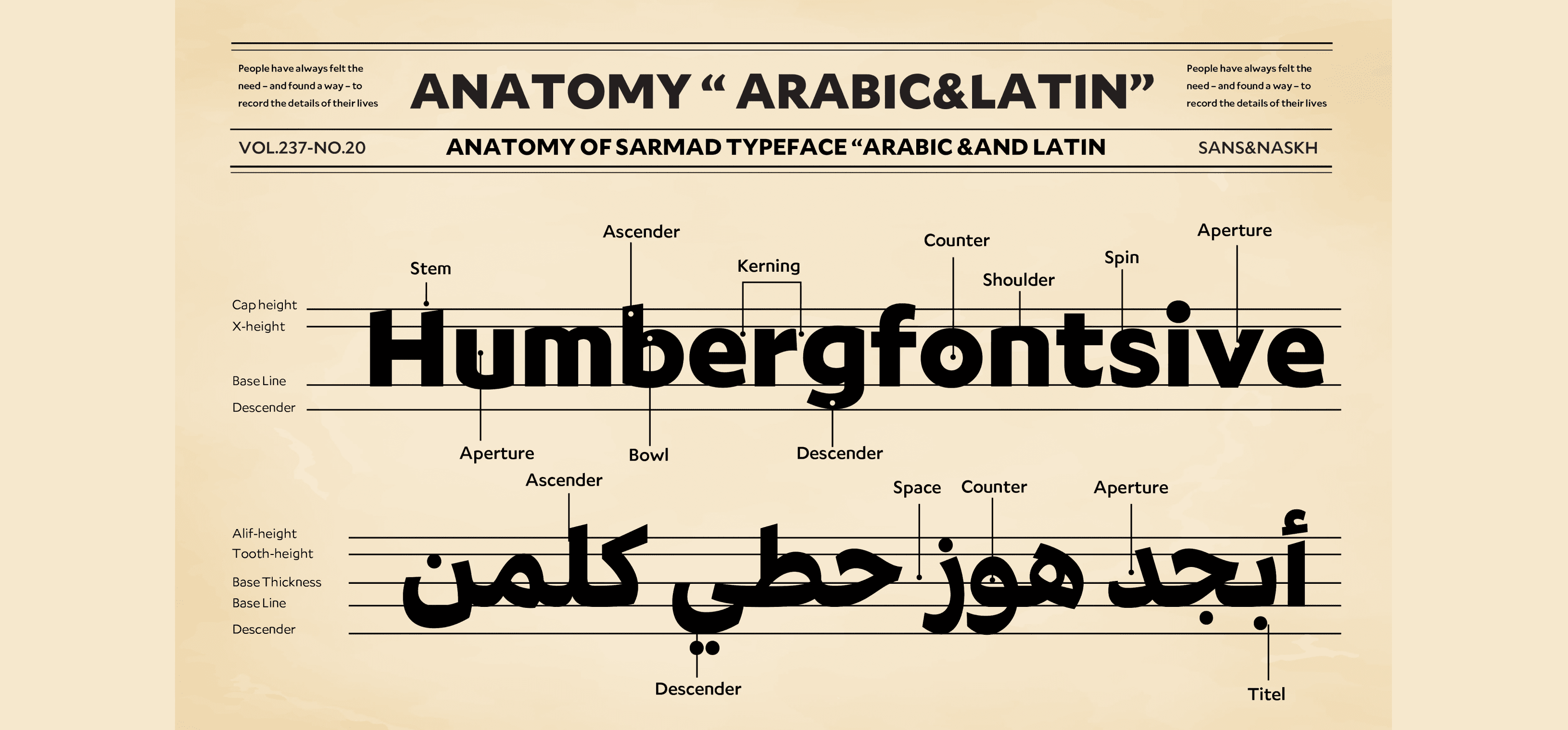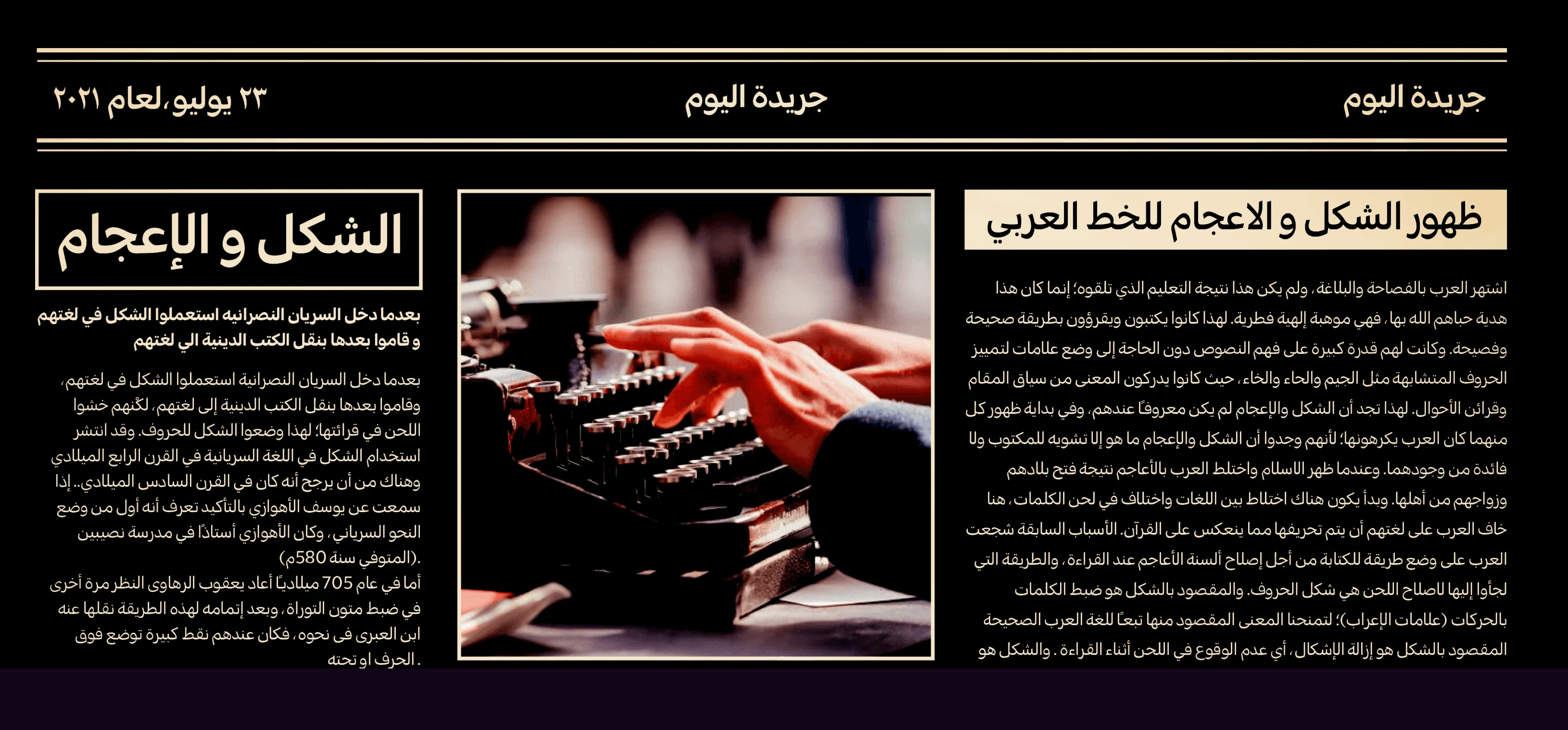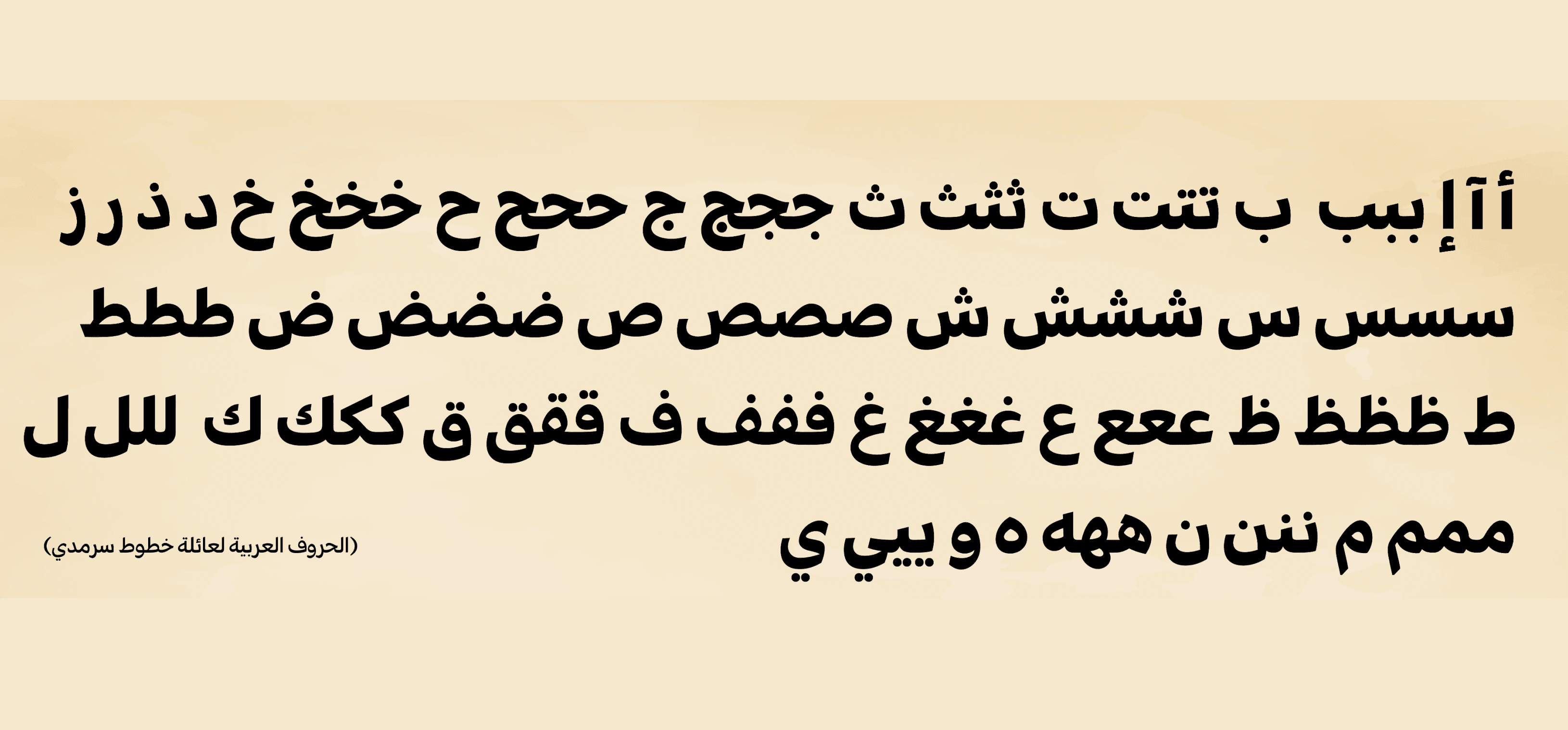
سرمدي هو النسخة الحديثة من الخط العربي القديم "النسخ"، وهو خط عصري قوي يجمع بين الأسلوبين: السانس والنسخ، في عائلة خطوط واحدة قوية تحتوي على 9 أوزان مختلفة تبدأ من النحيف وحتى العريض، مع جميع خيارات المائل.
يدعم سرمدي أكثر من 50 لغة تتنوع بين الأردية، الفارسية، الإسبانية، التركية... وغيرها، ويمكن استخدامه في التطبيقات الرقمية والمطبوعة.
سرمدي هو النسخة الحديثة من الخط العربي القديم "النسخ"، وهو خط عصري قوي يجمع بين الأسلوبين: السانس والنسخ، في عائلة خطوط واحدة قوية تحتوي على 9 أوزان مختلفة تبدأ من النحيف وحتى العريض، مع جميع خيارات المائل.
يدعم سرمدي أكثر من 50 لغة تتنوع بين الأردية، الفارسية، الإسبانية، التركية... وغيرها، ويمكن استخدامه في التطبيقات الرقمية والمطبوعة.
سرمدي هو النسخة الحديثة من الخط العربي القديم "النسخ"، وهو خط عصري قوي يجمع بين الأسلوبين: السانس والنسخ، في عائلة خطوط واحدة قوية تحتوي على 9 أوزان مختلفة تبدأ من النحيف وحتى العريض، مع جميع خيارات المائل.
يدعم سرمدي أكثر من 50 لغة تتنوع بين الأردية، الفارسية، الإسبانية، التركية... وغيرها، ويمكن استخدامه في التطبيقات الرقمية والمطبوعة.